随着科技的不断进步,自学生离开校园迈入社会之后,能够写字的机会也越来越少了,很多人都会出现“提笔忘字”的情况,而对于学生而言,字迹的好坏也是衡量学生的标准之一。
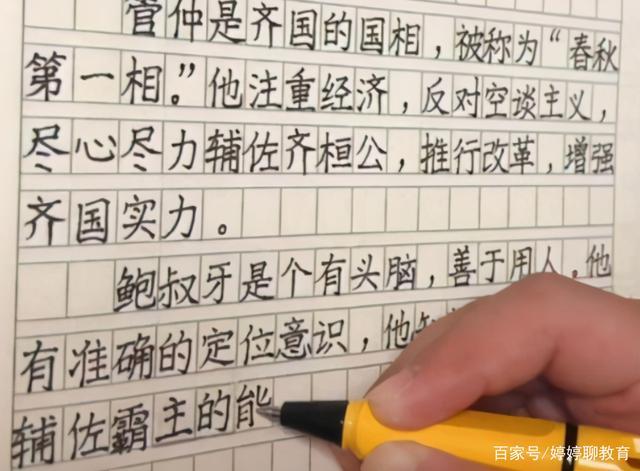
学生的字迹对于学生都有哪些影响?
第一点,试卷清晰工整,获得额外的卷面分。学生的字迹工整清晰的话,那试卷整体的完成度也会很好,从而获得阅卷老师的青睐,获得额外的加分。
第二点,能够得到他人青睐的目光,获得良好的人缘。对于学生而言,当自己写的一手好字的时候,那也会获得别人的青睐或羡慕的目光,从而让自己的地位得到很大的提升。
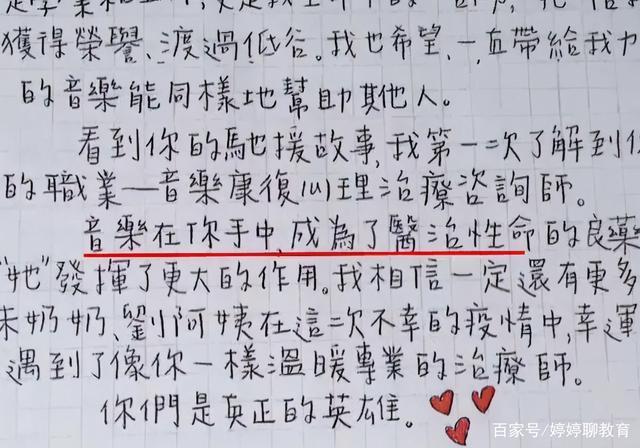
第三点,有利于复习知识点,更好的提升成绩。学生在学习时所记得课堂笔记,对学生的意义很大,而当学生字迹工整时,也能够清晰的辨认知识点内容,而不是自己写的什么内容都看不出来,更何谈复习呢。
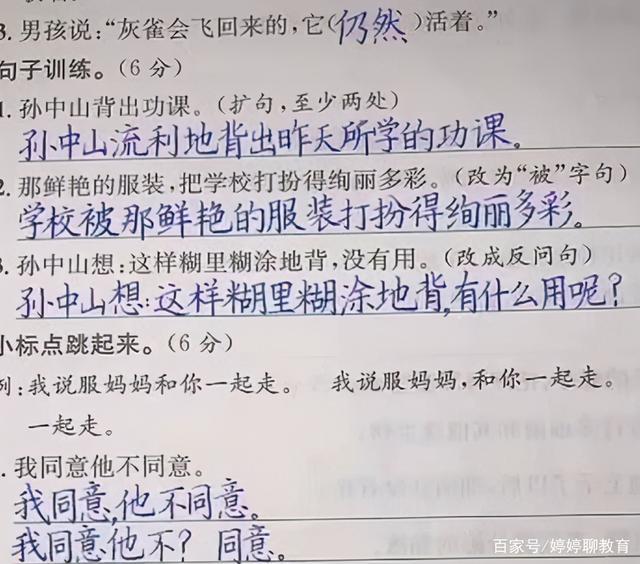
“奶酪字体”和“衡水字体”,差距过于明显
学生时期,大多数的老师都比较欣赏“衡水字体”,学生写的字迹比较工整,答案也是一目了然,不论是阅读还是判卷都能够有一个良好的感官。
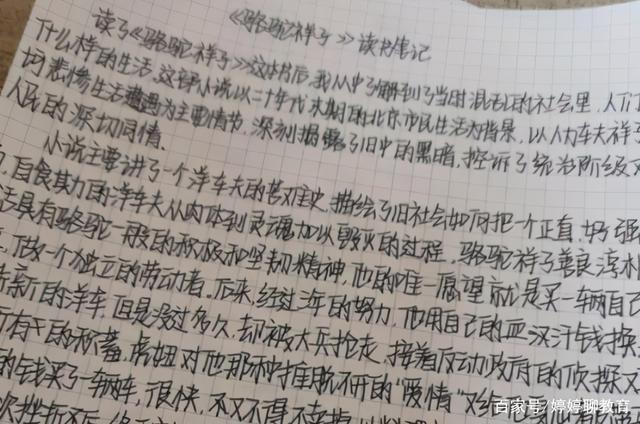
而学生的思维和想法也是在不断进步的,学生之间盛行的“奶酪字体”,也深受着学生们的喜爱,这类字体和名字一样,看上去也比较工整可爱。
奶酪字体虽然工整又个性,但容易有错别字
这类字体看上去很工整,并且还带点可爱洒脱的感觉,所以也受到了许多学生的欢迎,而且这类字体的特点就是简化,比如将“口”字简写,所以书写的速度也比较快。
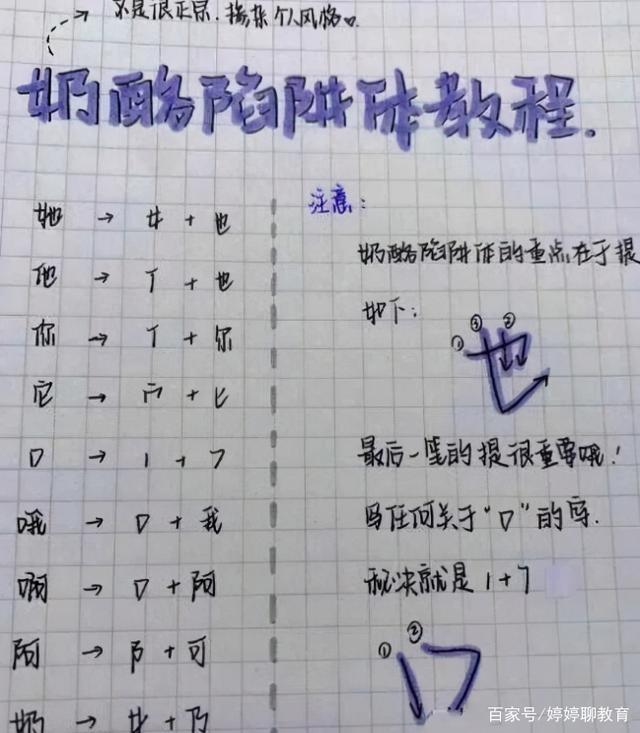
但也正是因为字体简化,学生也很容易有错别字,而且不利于学生识字认字,若是出现错别字的话,在考试时也可能会扣冤枉分。
衡水字体犹如“印刷体”,风格落落大方
对于学生而言,衡水字体可以说是很常见了,很多学生从小便开始练各种的衡水字帖,这类字体不论是写汉字还是英文,都比较工整,就犹如“印刷体”一样,看上去简洁明了,答案也是一目了然,所以也受到许多老师的青睐。
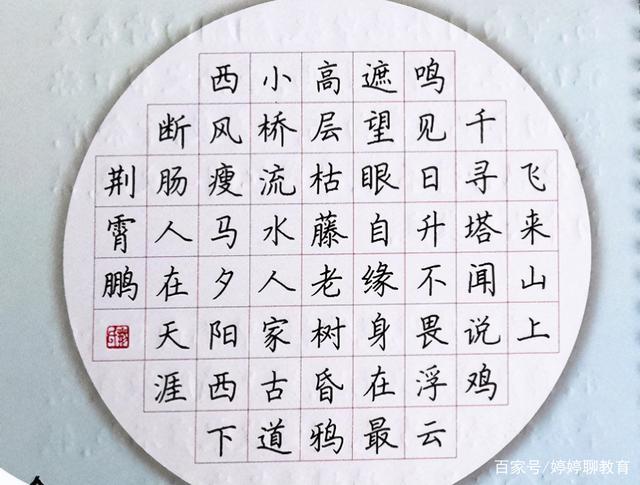
在判卷的时候,学生的答案和字体是同等重要的,若是学生的字体凌乱潦草,那也不利于整体的卷面分,很容易就会被扣分,而衡水字体则不会有这种担心,反而可能会获得加分。
综上所述,“奶酪字体”和“衡水字体”,没有对比就没有伤害,差距真的是过于明显了,好坏也是一目了然,所以还是衡水字体更加受到老师的青睐,老师也直言,在判卷的时候更愿意看到学生写衡水字体。
不论是从卷面的整洁度,还是试卷的完成度,都是衡水字体要更美观一些,所以学生们尽量不要模仿奶酪字体了,若是写出错别字就不好了,说不定考试还会被扣分。
工整规范的字体最重要,学生不要一味的去模仿
第一点,工整规范的字体能够培养学生良好的学习习惯。学习习惯对于学生而言意义非凡,可以说习惯影响着学生的成绩,而当学生的字体能够做到工整规范时,学生的学习习惯也会变得很端正。
第二点,老师与他人能够清晰的辨认即可,而不是一味的追求连笔字。尤其是小学生,只要写字工整规范,能够让老师和其他的同学清晰的辨认就行,而不是非要模仿大人或老师书写连笔字。
学生养成良好的书写习惯,离不开家长的日常指导
学生从小便开始练字,而在练字的过程中,也离不开家长的日常指导,若是只对照字帖练字的话,那学生的字体也会“千篇一律”,没有个人的特色,很容易吃亏。
而学生养成良好的书写习惯,也和家长的指导有很大关系,所以家长在关注学生成绩的同时, 也要在乎学生的字体,争取让学生锻炼出有自己风格的字体。
都说“字如其人”,学生若是想要获得他人的青睐和认可,也要练出工整优美的字体,当学生的字体能够让老师或他人赞赏的时候,也意味着学生的字体练到家了。
笔者个人寄语:对于学生而言,不仅学习成绩重要,字体也十分的重要,所以学生在提高成绩的同时,也要将自身的字体练好才可以,两者都不能落下。